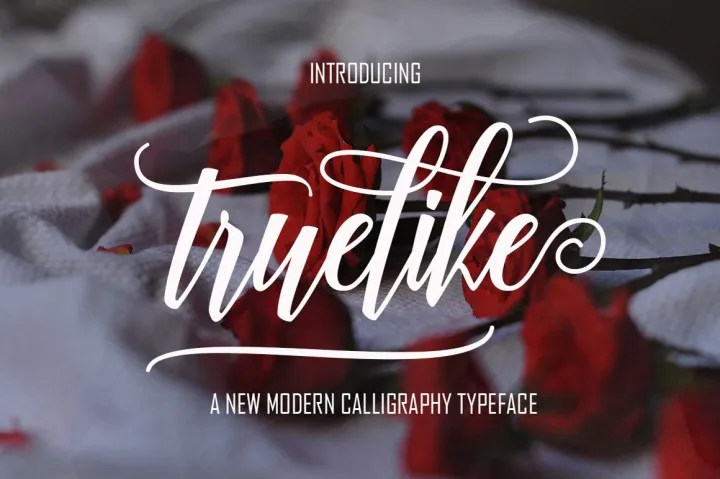
Truelike Script Font – Download Grátis
Introduzimos a Truelike Script Font! Esta elegante e sofisticada tipografia foi criada pelo designer da Pollem.Co e está disponível gratuitamente para download hoje, após ter sido disponibilizada anteriormente por um preço. A Truelike Script é uma fonte premium, perfeitamente adequada para trabalhos que desejam transmitir elegância e estilo. Ela é perfeita para aplicações de logotipo sofisticadas, capas de revistas, cartões de visita, anúncios e qualquer tipo de uso online. A Truelike Script foi projetada para ser uma fonte de conectação que funciona incrivelmente bem tanto em marcas de moda quanto em blogs de tendências e empresas desejando destacar-se com classe e elegância. Além disso, ela é perfeita para cartões de agradecimento, cartazes, folhetos e todas as aplicações web onde seja necessário usar um estilo elegante.